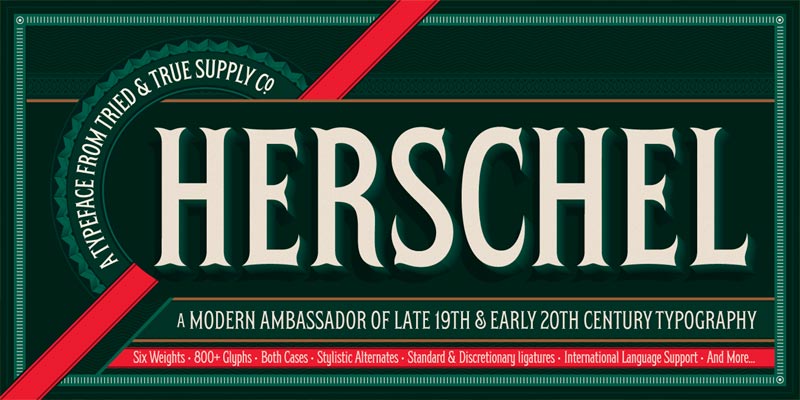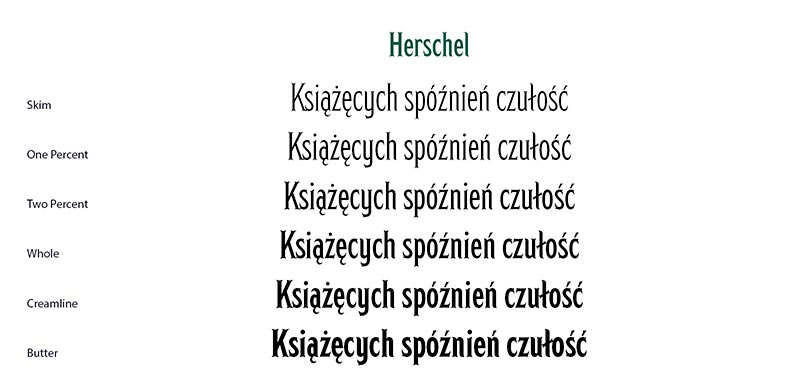
Font Herschel
Zakupiliśmy ozdobny font projektu Briana Brubakera ze Stanów Zjednoczonych. Liternictwo nawiązuje do 19-sto wiecznej typografii. Zestaw posiada polskie znaki diakrytyczne i składa się z 6 odmian grubości.